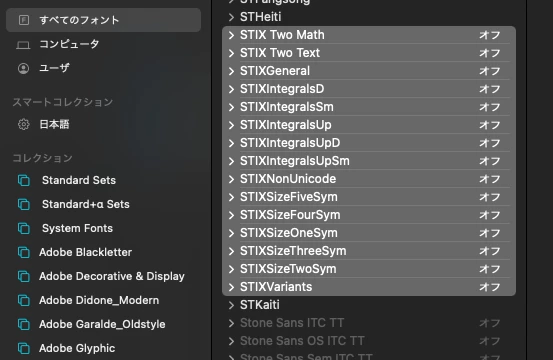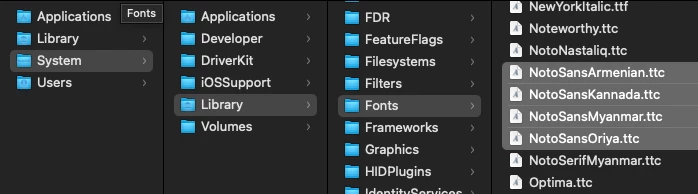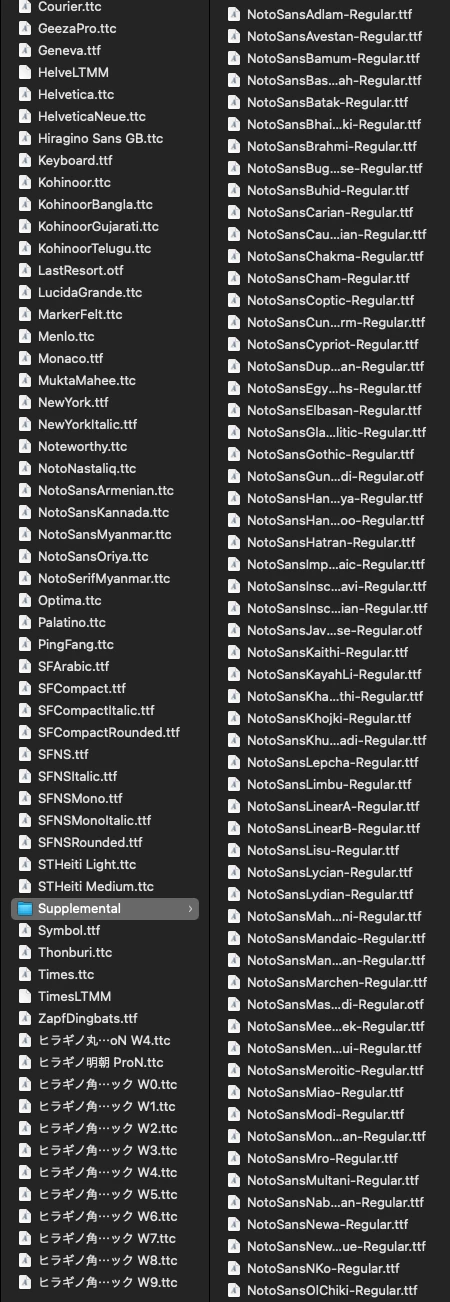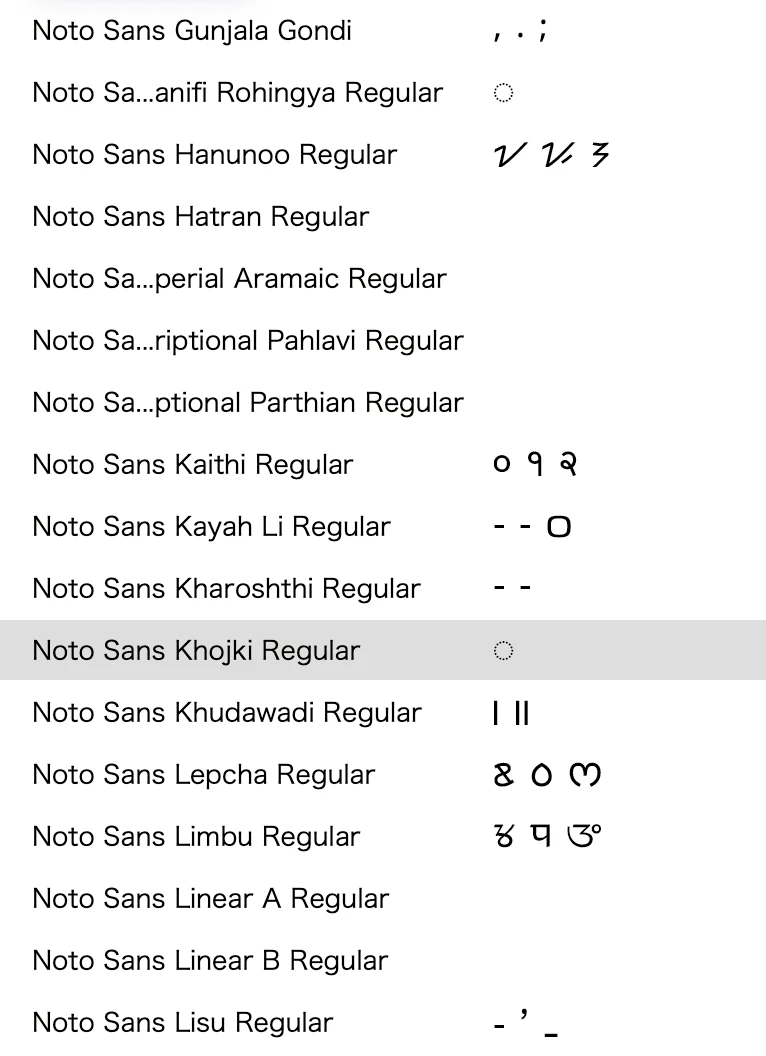
また NotoSans は各国語の補足フォントでありますからテキストエディットなどの Mac 標準アプリからは見えないようになっています。そのため FontBook からは見えないためオフにすることもできません。
Notoも、STIXも、全ての言語、学術、世界の人々を漏れ無くサポートするという大義ですので、ある程度我慢するしかないかも。SDGsみたいな感じかな。
Noto fonts(ラテン語で書く、印をつける、メモする、もしくは no tofu 豆腐なし)
Google、Adobe、イワタ等。世界の言語をサポートし豆腐文字(□□□)を排除し、全ての人(800言語11万字以上)と文章を共有できる環境を目指す。
STIX fonts(Scientific and Technical Information Exchange)
STIXフォント作成プロジェクトの使命は、原稿の作成から最終的な出版までの過程で、電子形式と印刷形式の両方で科学技術コミュニティに役立つ包括的なフォントセットを準備する。
確かに、大切な役割を持ったフォントですね。
Adobe Fontではないので対処ができないということでしたので、
Appleにも質問してみました。
その結果なのですが、
Font Bookで検索して表示されるNoto Sansの数が
「Supplemental」フォルダ内にあるNoto Sansの数と合っていないのが
そもそもおかしいという話になりまして。。
Appleの方に私の画面を共有して一緒に確認したのですが、
Apple側のMacでは、Font BookのNoto Sansは全て表示されており、
私のMacでは、一部のNoto Sansしか表示されておりませんでした。
それを受けてのAppleの案内は、
まずはOSの再インストールをしてみてほしいということでした。
ただ、私の同僚数名(私と異なるOSです)も
Font Bookでは一部のNoto Sansしか表示されておらず、
イラレでは大量のNoto Sansが表示されておりますので、
OSの問題ではないように思うのですが。。
取り敢えず、OSは折りを見て再インストールしてみようとは思いますが、
あまり期待はしておりません。
やはり諦めるしかないように思います。。
Noto Sans は2箇所にあります。
1箇所は「/System/Library/Fonts/...」にあり
NoteSansArmenian.ttc を除いてFontBookに表示されています。これは本来のフォントでシステムフォントであることからオフにできません。NoteSansArmenian.ttc がなぜ FontBook に表示されないのかは不明です。
もう1箇所が「/System/Library/Fonts/Supplemental/...」にありFontBookに表示されません。
これは各国語の補足フォントであるので、その言語のフォントを使っていない限り役に立ちません。
Apple側のMacでは、Font BookのNoto Sansは全て表示されており
これはちょっと考えにくいことですね、通常のユーザーとは違う OS のような気がします。
それを受けてのAppleの案内は、
まずはOSの再インストールをしてみてほしいということでした。
これも間違ったアドバイスと思いますね。Monterey では書き換えの出来ないシステム領域と書き換えの出来るユーザーのデータ領域(ユーザーのインストールしたアプリなども含みます。)は明確に区分されていまして、通常はあり得ないことですがシステム領域が書き換えられても自動的に修復されて元に戻ってしまいます。
改善されるかはあまり期待せず、そのまま使って問題ないと思いますよ。
大変失礼いたしました。
STIXシリーズについては、
Font Bookで見落としていたようです。
OFFにすることができました!
NotoSansについては、
仰る通り削除することができませんでした。
お気に入りマークは
よく使う僅かなフォントのみに絞って付けているため、
NotoSans以外の全てのフォントに付けることができず。。
残念ですが、仕方がないものと割り切ることにいたします。
Notoシリーズはレガシーフォント絡みで/System/Library/Fonts/Supplementalあたりにありそうです。必要なければ単純に当該フォルダからバックアップの上削除してしまえば良いです。万が一必要な場合は戻せば認識します。STIX関連がたくさんあるのは数式処理関連の為にTexと共に利用するために用意したものではないかと思うのですが、その辺りの経緯がはっきりしないので現状必要なければ同様に削除する方向で良いでしょう。
NotoSansについては、
ご指摘いただいたフォルダにあったのですが、
削除することができませんでした。
(禁止マーク?が出てしまい、動かすことができませんでした。。)
Photoshopコミュニティの該当投稿の頃には削除ができて、
現在はできなくなってしまったのかもしれません。
残念ですが、仕方がないものと割り切ることにいたします。
STIXシリーズについては、
別の方からのご指摘でFont Bookでの見落としが発覚いたしました。
無事OFFにすることができました。